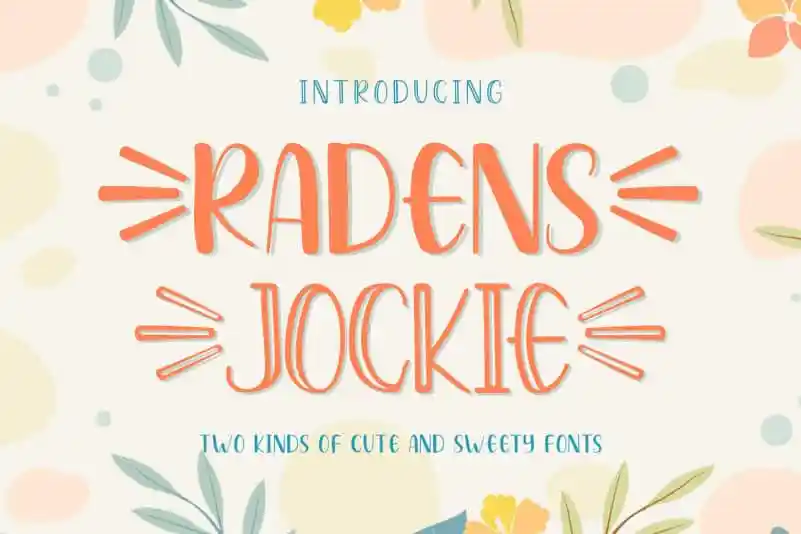
Radens Jockie Font – Download Grátis
A Radens Jockie Font é uma fonte escrita a mão que traz vida aos seus projetos criativos. Com dois estilos, regular e hollow, ela se destaca por sua elegância e encanto. Perfeita para quem busca adicionar um toque de inocência e originalidade em suas obras de arte manuscritas ou gráficas. Seja na decoração da casa, no design de arte digital ou até mesmo em projetos manuais, esta fonte convidativa é ideal para tornar seu trabalho ainda mais especial. Aproveite a sua criança interior com esses traços simples e charmosos, elevará qualquer projeto criativo para o próximo nível. Não hesite: deixe-se levar pelo encanto desta fonte única!